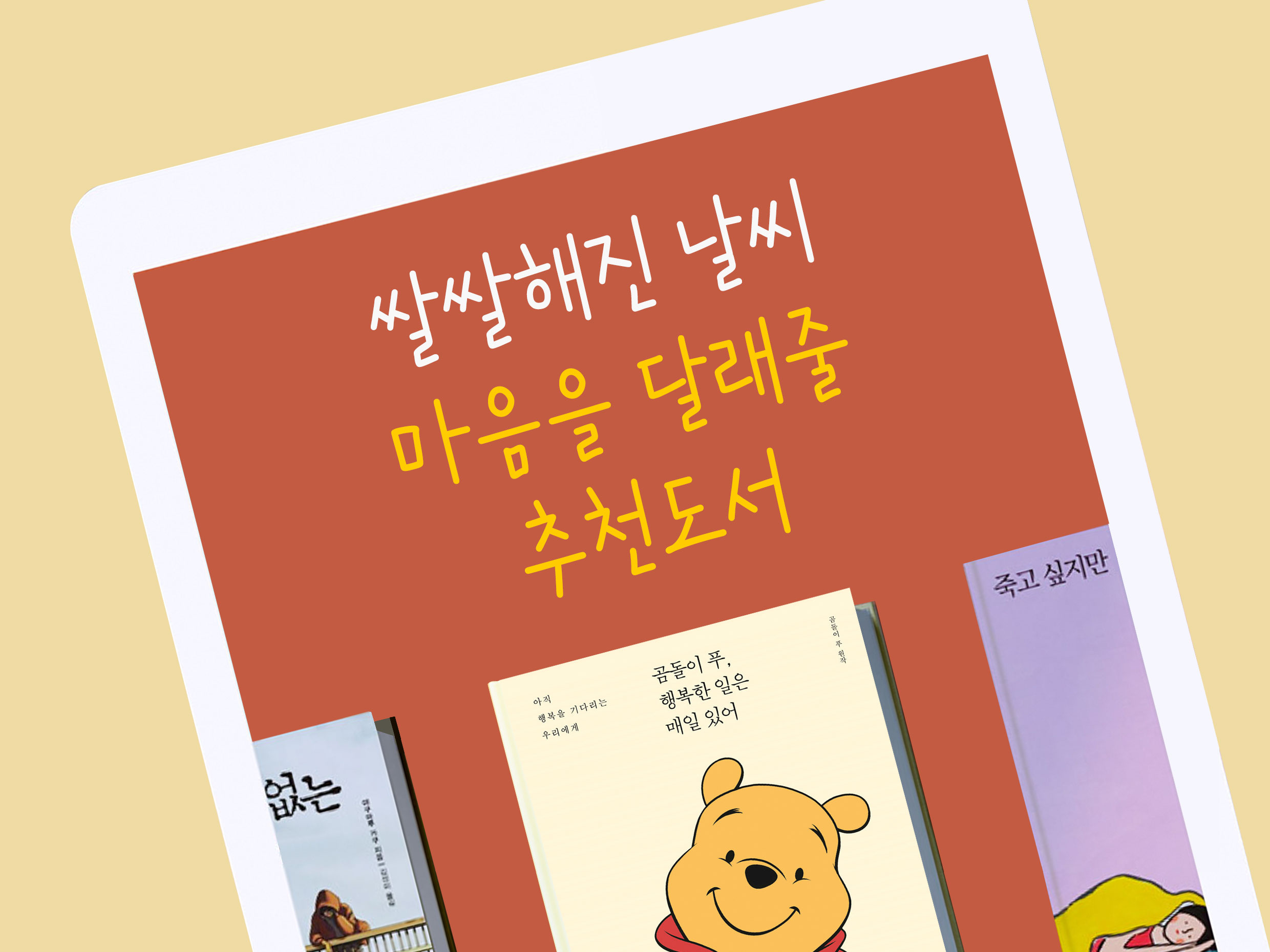
교보손글쓰기 [교보 손글씨 2021 성지영]
대산문화재단과 교보문고, 교보생명이 공동으로 매년 주최하는 ‘손글쓰기문화확산캠페인’을 통해 매년 하나씩 선정된 작품의 손글씨를 디지털 서체로 만들어 무료로 배포하는 프로젝트.
한글 11,172자 / 영문 95자 / KS특수문자 986자